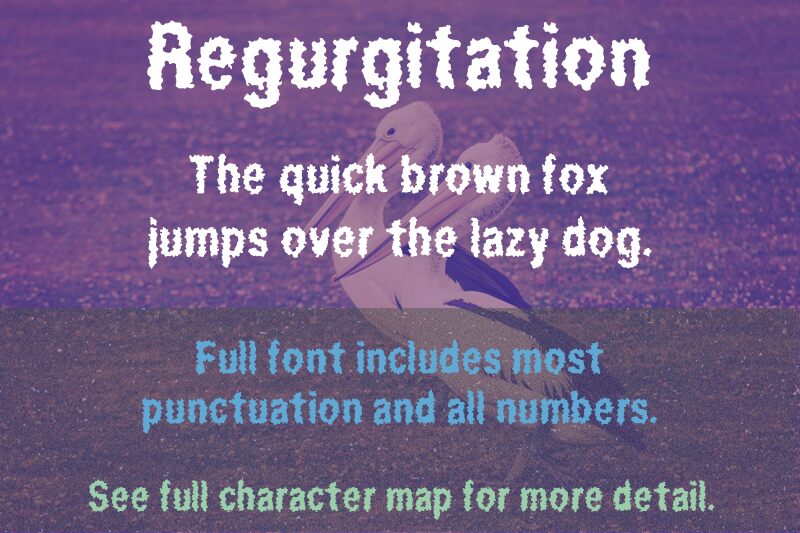
Regurgitation von Lauren C. Brown ist eine kostenlose, verzerrte Display-Schriftart mit einem schmuddeligen, schmelzenden Horror-Vibe. Die Buchstaben wirken gleichzeitig aufgedunsen und zerfressen, mit ausgefransten Kanten und weichen Tropfen, die das Alphabet eher wie Schleim, Schimmel oder etwas beunruhigend Organisches wirken lassen als wie gewöhnliche Schriftzeichen.
Das macht sie zur perfekten Wahl für Horror-Poster, Zine-Cover, Underground-Band-Artworks, Halloween-Flyer und Titelkarten, bei denen das Wort selbst kontaminiert wirken soll. Da es sich um eine kostenlose Schrift handelt, funktioniert sie am besten in kurzen Überschriften, Logos oder als einzelner, fieser Initialbuchstabe, denn die massiven, verfallenen Formen transportieren die Stimmung, noch bevor man das Wort liest.
Die Schriftart Regurgitation wurde erstmals Ende 2000 veröffentlicht.
- Groß- und Kleinbuchstaben
- Zahlen
- Satzzeichen